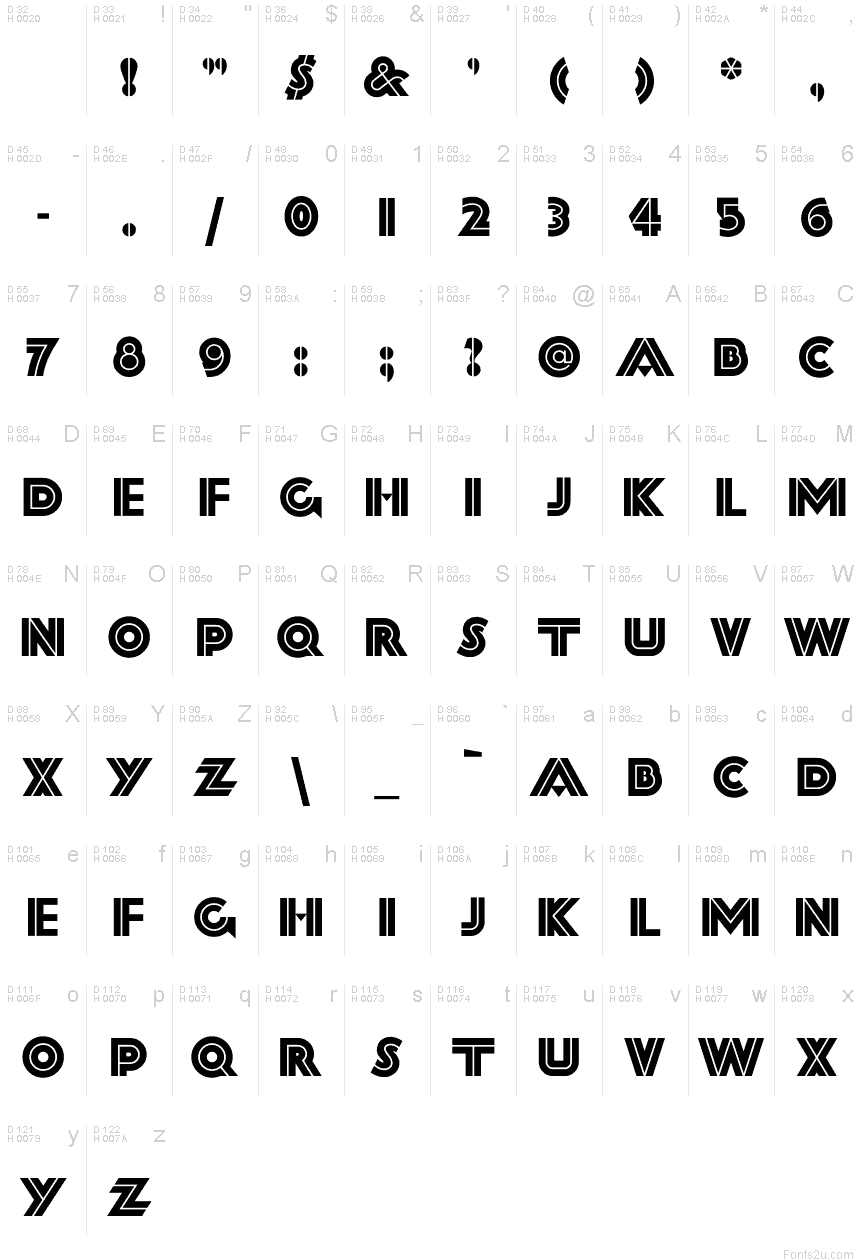
FortySecondStreetHB
Forty Second Street HB autorstwa Nicka Curtisa to darmowy, utrzymany w stylistyce groovy font typu display, który przenosi Cię prosto na neonowy szyld. Grube, blokowe litery uderzają głęboką czernią, a „O” przypominające tarczę strzelniczą i ostro wycięte „Y” nadają każdemu słowu śmiały, teatralny charakter. Całość jest wyrazista i sceniczna – niczym nagłówki krzyczące na ruchliwej, nocnej ulicy.
Forty Second Street HB świetnie sprawdzi się na plakatach retro, ulotkach klubowych, okładkach albumów, w identyfikacji wizualnej teatrów, odważnych logotypach czy wyrazistych grafikach do mediów społecznościowych. Dzięki ciasnemu rytmowi i solidnym wypełnieniom, ten darmowy krój pisma błyszczy w dużych rozmiarach, gdzie jego graficzne kształty mogą w pełni wybrzmieć. Zestaw go z lekkim, bezszeryfowym krojem w tekście głównym i pozwól, by Forty Second Street HB przejął rolę przyciągającego uwagę akcentu.